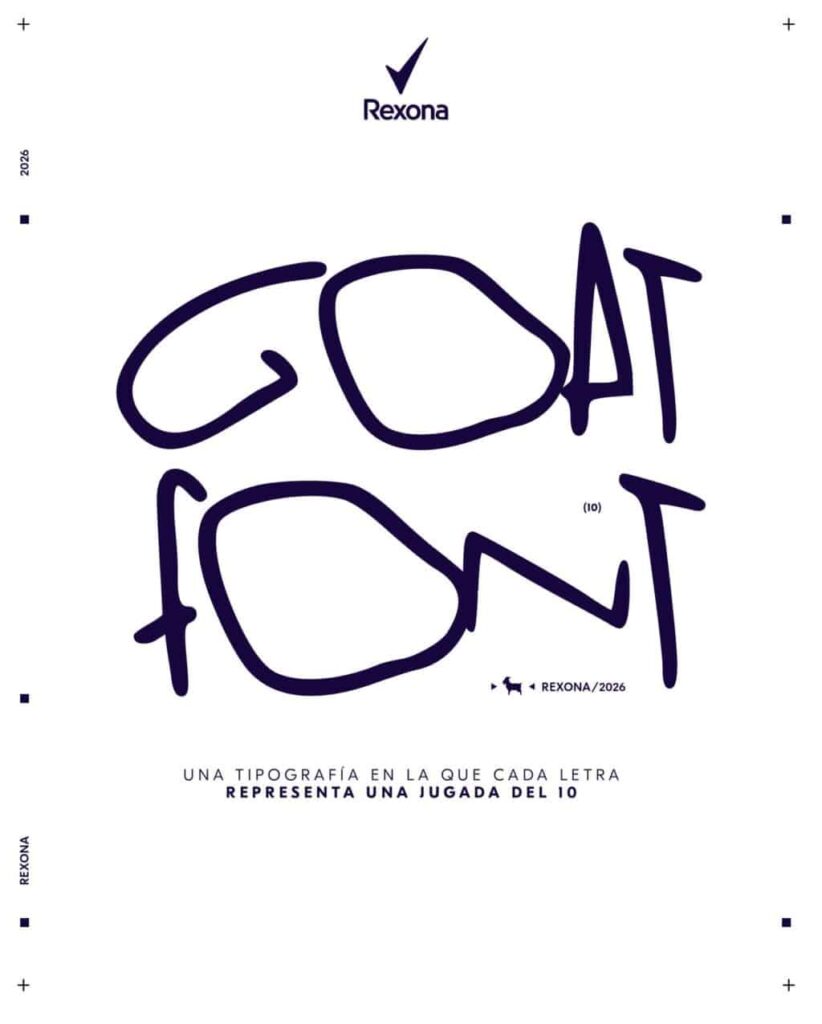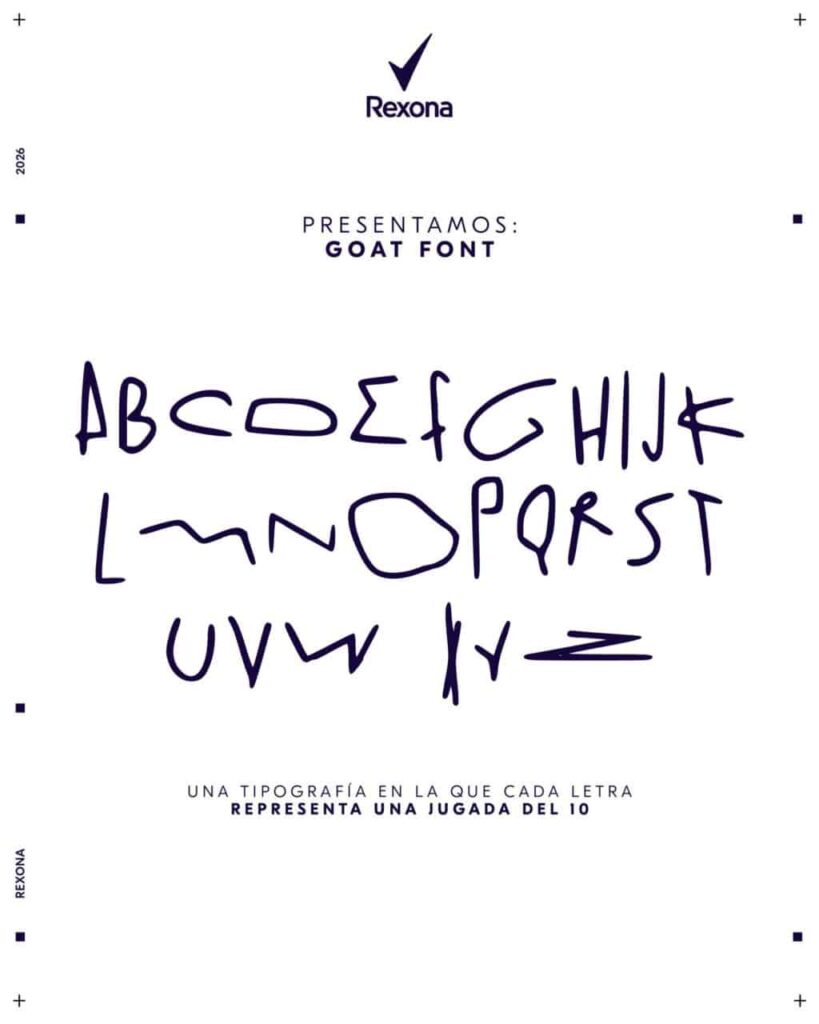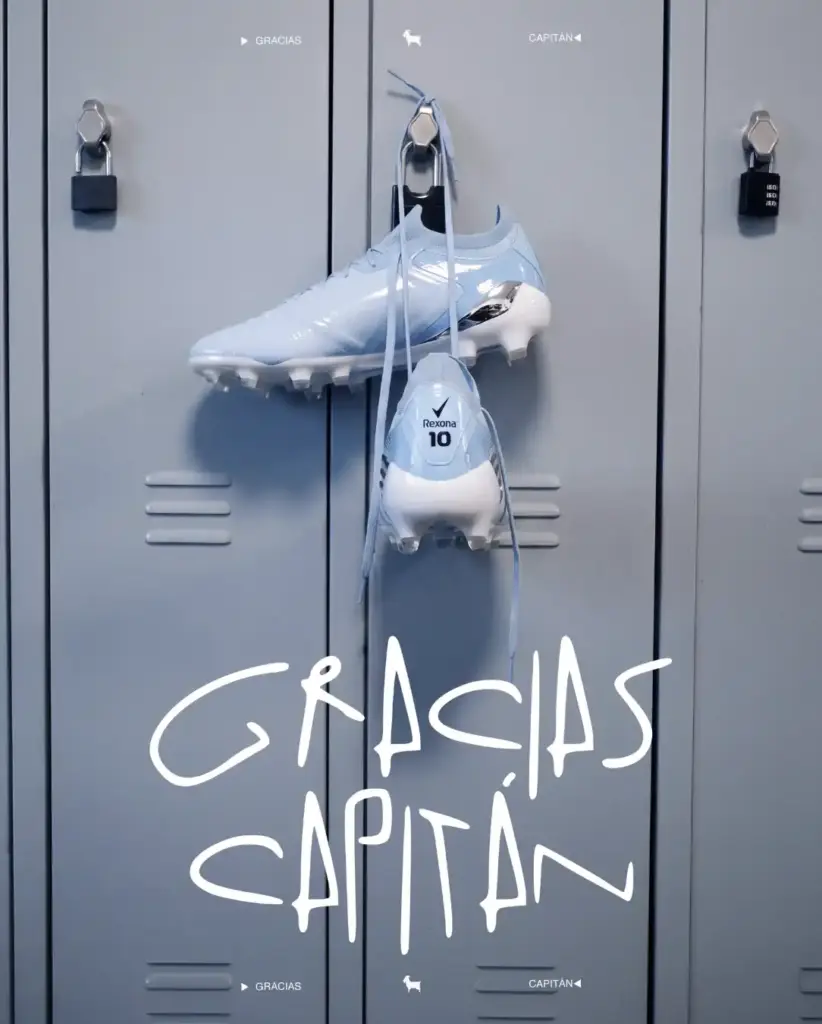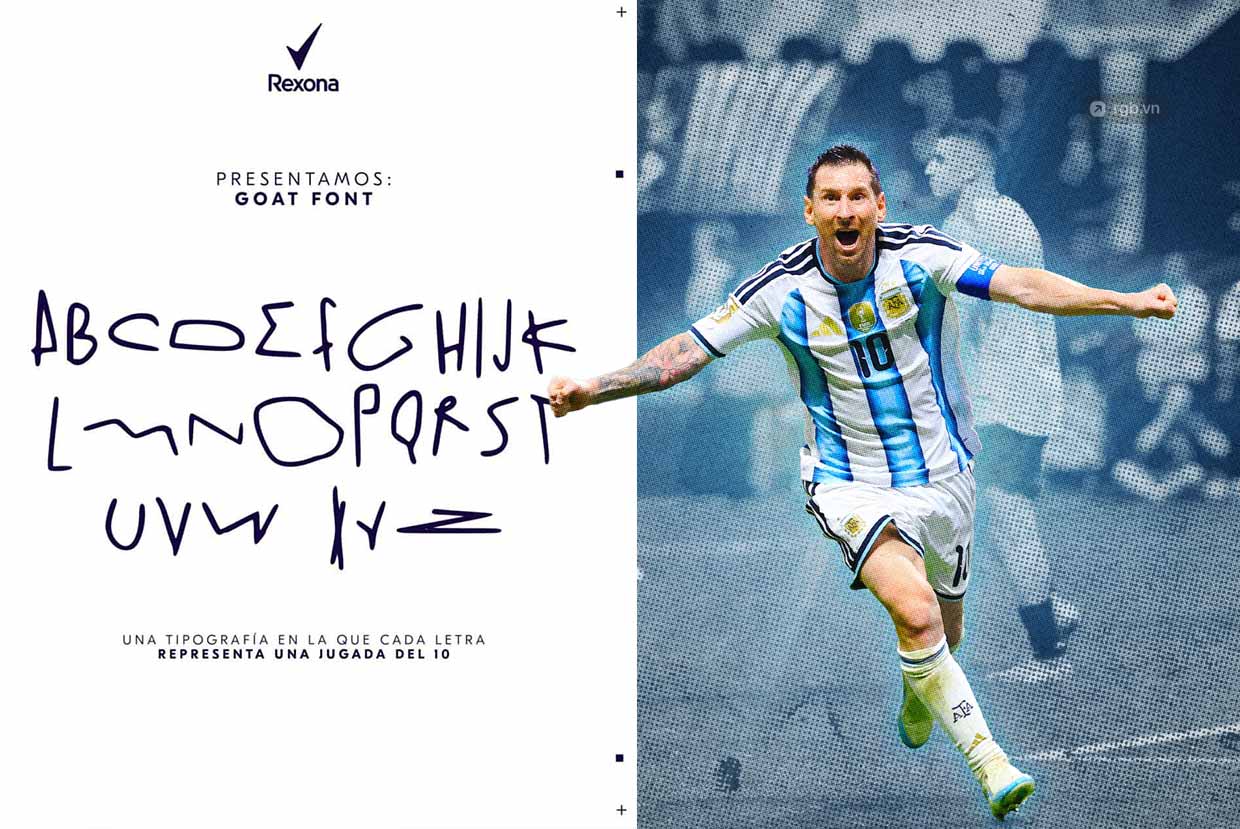
Những pha rê bóng làm nên tên tuổi Lionel Messi giờ đây được Rexona biến thành… một bảng chữ cái. Rexona Argentina vừa giới thiệu GOAT Font, bộ typeface đặc biệt lấy cảm hứng từ những pha bóng có thật của Messi trong màu áo đội tuyển Argentina để tạo nên từng ký tự.
Dự án được ra mắt không lâu sau khi Messi thông báo chia tay đội tuyển Argentina vào ngày 31/8. Ở tuổi 39, anh khép lại sự nghiệp quốc tế bắt đầu từ năm 2005 với 125 bàn thắng sau 207 lần ra sân, cùng hai chức vô địch Copa América vào năm 2021 và 2024, cũng như chức vô địch World Cup 2022.
Thay vì mô phỏng chữ viết tay của Messi, GOAT Font biến chính những chuyển động của anh trên sân thành cấu trúc thị giác. Mỗi ký tự được xây dựng dựa trên quỹ đạo của một tình huống có thật khi Messi khoác áo Argentina: từ những cú đổi hướng, rê bóng cho đến các đường chạy đều được chuyển hóa thành những nét chữ.
Tên gọi GOAT Font bắt nguồn từ cụm “Greatest of All Time” – danh xưng thường được dùng khi nhắc đến Messi. Một số ký tự uốn cong đột ngột, số khác tạo thành vòng lặp hoặc quay ngược trở lại, gợi nhớ những đường đồ họa thường được sử dụng để mô phỏng quỹ đạo di chuyển của cầu thủ trên sân.
Nhà thiết kế Pedro Destefano được cho là đã kết hợp trí tuệ nhân tạo với phương pháp tracing thủ công để tái dựng những tình huống này, sau đó tinh chỉnh chúng thành các glyph có thể sử dụng như một bộ font thực sự.
Mỗi con chữ còn là một câu đố dành cho fan Messi
Rexona còn cố tình để lại một trò chơi nhỏ bên trong thiết kế. Thương hiệu không công bố đầy đủ trận đấu hay tình huống nào tương ứng với từng ký tự, để người hâm mộ tự đối chiếu hình dạng của chúng với những thước phim cũ trong sự nghiệp của Messi tại đội tuyển Argentina.
Từ những đường chạy từng xuất hiện trên sân cỏ đến những nét chữ có thể gõ trên máy tính, GOAT Font biến dấu ấn trong sự nghiệp của Messi thành một ngôn ngữ thị giác theo đúng nghĩa đen.